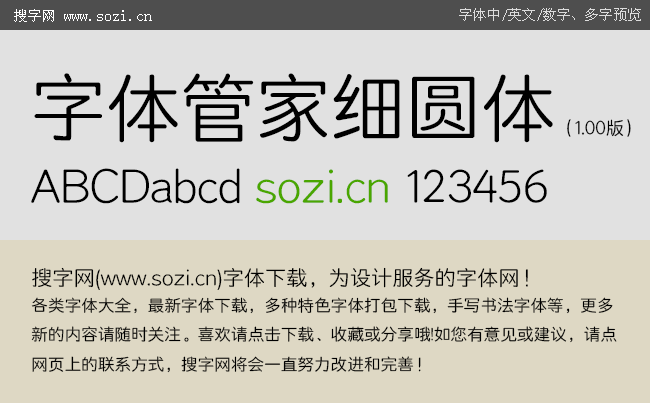
字體管家細(xì)圓體
搜字網(wǎng)提供字體管家細(xì)圓體中文字體下載,字體管家細(xì)圓體是一款應(yīng)用于設(shè)計方面的中文簡體漢字,該字體字體端正簡潔,整體效果十分出色,可以應(yīng)用于廣告設(shè)計、名片設(shè)計、包裝印刷、產(chǎn)品設(shè)計等應(yīng)用。